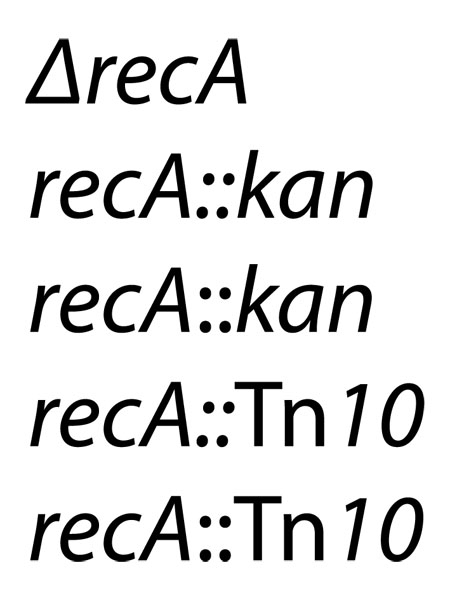
Ich muß gerade eine ziemlich umfangreiche Tabelle setzen, in welcher Bakterienstämme aufgelistet werden, in welchen bestimmte Gene ausgeknipst wurden. Die Kurzformen von Gennamen werden in der Genetik immer kursiv geschrieben, z.B. recA. Wurde ein Gen ausgeknipst, so kann man dies allgemein mit einem ? kenntlich machen, also z.B. ?recA. Man kann allerdings auch den Marker angeben, durch welchen das Gen ausgeknipst wurde, also z.B. eine Resistenz gegen das Antibiotikum Kanamycin. Dies wird durch das Anhängen eines doppelten Doppelpunktes und die Kurzform der Resistenz erreicht, z.B. recA::kan. Das ist alles Konvention und stellt kein Problem dar. Perfiderweise gibt es jetzt aber einen Sonderfall, in welchem ein ganz bestimmtes Stück DNA in das Zielgen gesetzt wurde, ein sogenanntes Transposon. Diese wurden nummeriert. Die Kurzform ist daher »Tn« und dann die Nummer. Aus historischen Gründen wird nun das »Tn« aufrecht, die Nummer aber kursiv gesetzt, also z.B. Tn10. Und jetzt die Preisfrage: Wenn ich ein Gen durch ein solches Transposon ausschalte, dann gibt es im Satz zwei Möglichkeiten dies darzustellen; einmal kann ich den doppelten Doppelpunkt aufrecht lassen wie das Tn, einmal kann ich es kursiv setzen wie das Gen. Hier gibt es einfach keine Konvention und jeder macht es so, wie es ihm gerade einfällt. Manche werden auch verunsichert und schreiben den doppelten Doppelpunkt plötzlich immer aufrecht. Wenn es nun keine Konvention gibt, dann kann ich aber auch einfach die ästhetisch ansprechendste Lösung finden. Wie würdet Ihr Euch entscheiden, wenn Ihr die Tabelle setzen müßtet?
recA::Tn10
Und falls es die letzte Variante sein soll: Würdet Ihr das dann auch bei einfachen Markern einheitlich machen? Oder würdet Ihr da bei der komplett kursiven Variante bleiben?
recA::kan
Aufgrund des Umfanges ist die Tabelle ziemlich klein gesetzt (8–9 pt), hier aber trotzdem noch mal eine Vergrößerung.
Ich würde zu den aufrechten Doppeldoppelpunkten greifen und diese durchgängig verwenden, auch wenn davon und danach kursiv gesetzt ist. Quasi als "Ausknipssonderzeichen".
Ja, das habe ich auch schon überlegt. Leider sperrt es sich in der komplett kursiven Schreibweise etwas (zumindest bei dem Beispiel in Myriad Pro steht bei recA::kan der letzte Doppelpunkt zu dicht am »kan«), aber es wäre zumindest einheitlich. Aufgrund der geringen Größe fällt das vermutlich sowieso nicht sonderlich stark auf und es hat zusätzlich den Charme daß sich die Tabelle einfacher setzen läßt, weil man unkompliziert über »Suchen/Ersetzen« einheitlich austauschen kann.
Ich würde inhaltlich, nicht ästhetisch, rangehen:
Wenn ich es richtig verstanden habe, dann ist das aufrechte „Tn“ ein Sonderfall. Gäbe es ihn nicht, wäre alles kursiv. Und so würde ich es auch mit dem Doppeldoppelpunkt halten …
Kursive Doppelpunkte sehen dann am besten aus, wenn alles andere auch kursiv ist, sie passen aber bei manchen anderen Kombinationen überhaupt nicht. Die geraden Doppelpunkte dagegen lassen sich aber insgesamt doch bei allen Kombinationen gut ansehen. Also würde ich ganz einheitlich immer die nehmen, dann braucht man sich auch nicht irgendwelche Regeln zu merken, wann kursiv und wann gerade.
Ich würd auch die geraden nehmen. Da es ja zwei nebeneinander sind, stützen sie sich gegenseitig (und für mich, die ich doppelte Doppelpunkte nicht gewohnt bin, sieht das ein wenig aus wie ein einziges quadratförmiges Pünktelsonderzeichen – nett). Ein einzelner Doppelpunkt würde als schmales Satzzeichen vermutlich sehr viel mehr «aus dem Rahmen fallen», wäre er an dieser Stelle nicht kursiv.
ist das wirklich ein doppelter Doppelpunkt? Ich meine, nur weil es üblich ist, das so zu machen, heißt ja nicht, dass es auch korrekt ist, ne?
Versteh' das nicht als Kritik oder so, ich habe ja keine Ahnung, aber mich würde es interessieren, ob es dafür nicht ein extra Symbölchen gäbe. Womöglich so, dass die Punkte ein Quadrat bilden, so wie die \squaredots aus dem MnSymbol-Pakte von LaTeX. In der Dokumentation zu bewundern auf Seite 7.
ist das wirklich ein doppelter Doppelpunkt?
Ich habe ehrlich gesagt nicht den Schimmer eine Ahnung, wann dieses Zeichen eingeführt wurde und wer das gemacht hat und ob dafür extra ein Zeichen definiert wurde oder nicht. Seit Jahren kursiert es in der Fachliteratur und ist, zumindest in der Praxis, immer ein doppelter Doppelpunkt, was Anderes können Wissenschaftler nicht! :wink:
In den Fachzeitschriften ist dies ähnlich, denn da durchaus mal die kursive und mal die aufrechte Variante gewählt wird, ist es einfacher und hat sich einfach eingebürgert (zumindest in den pdfs der gängigen Artikel ist dies so). Ich wage zu bezweifeln, daß es für das Zeichen \squaredots noch eine kursive Variante gibt, oder?